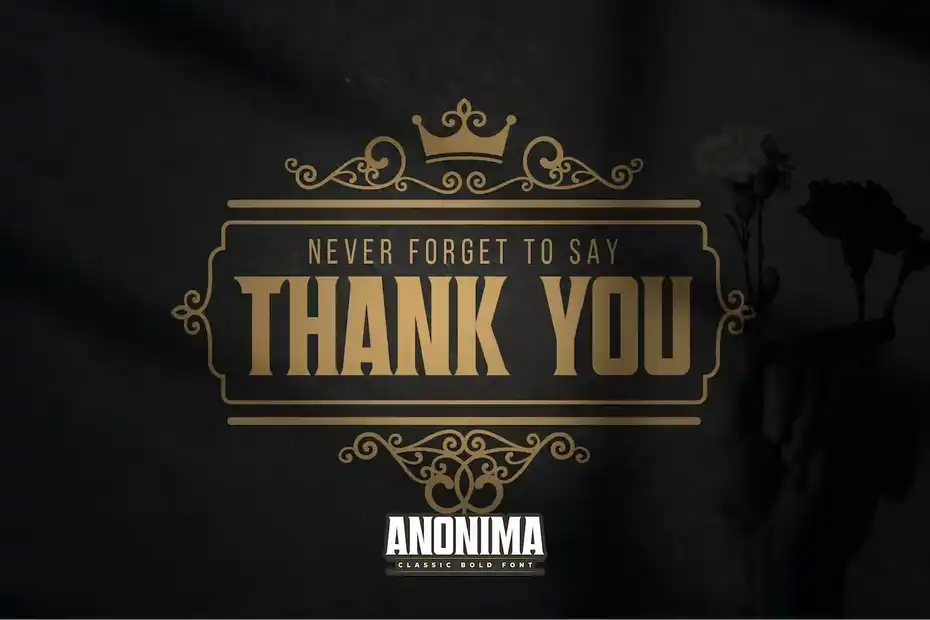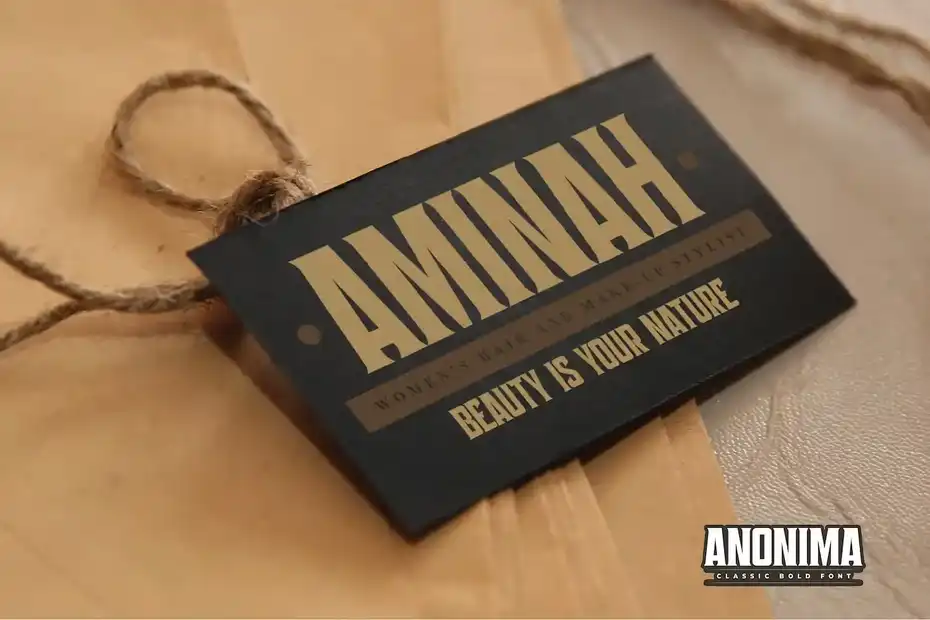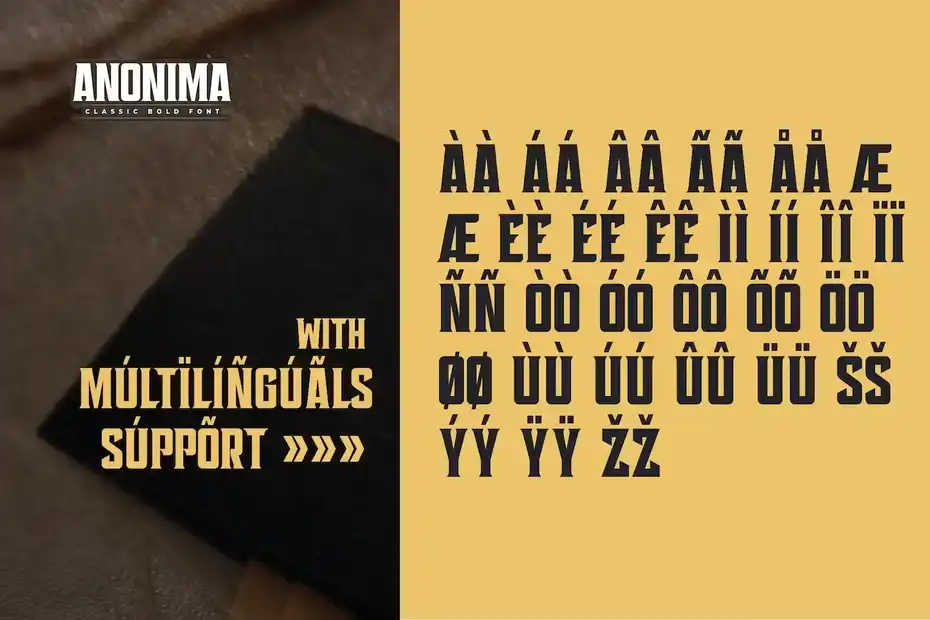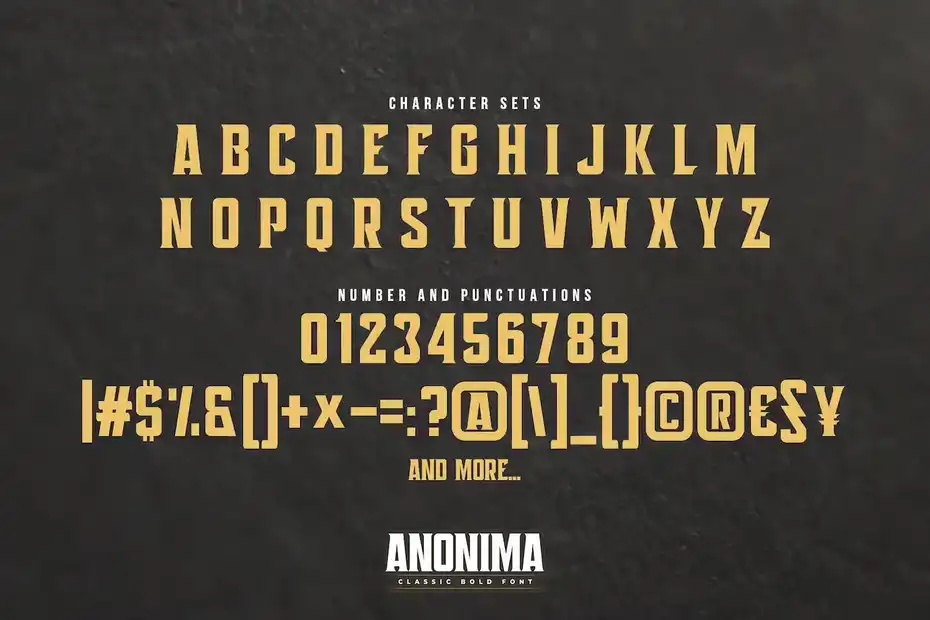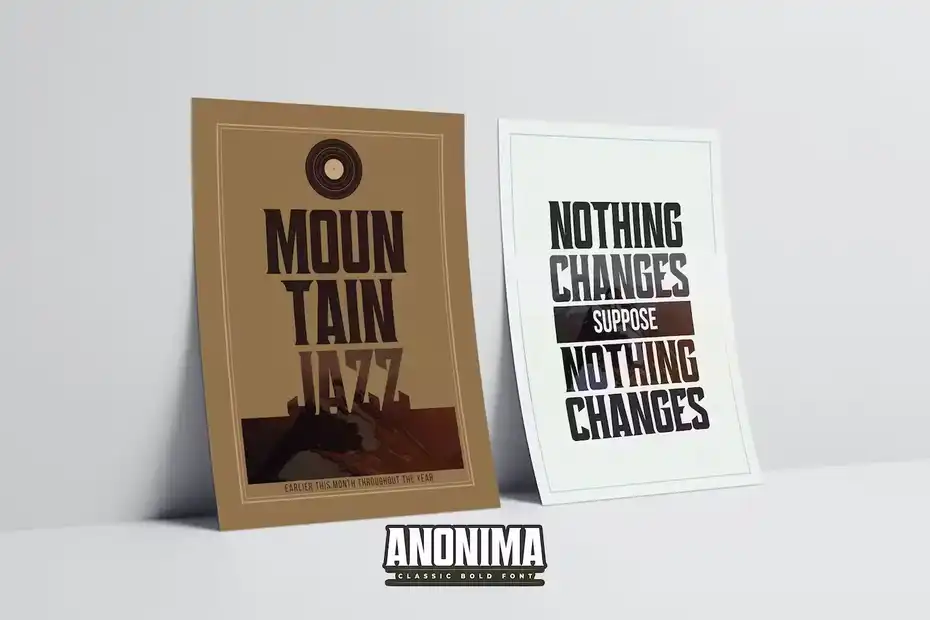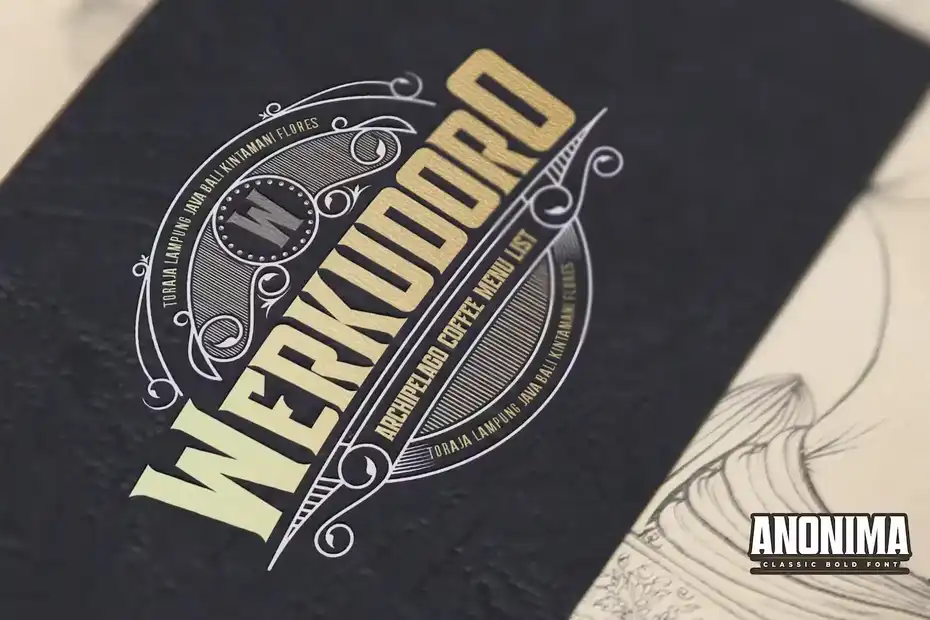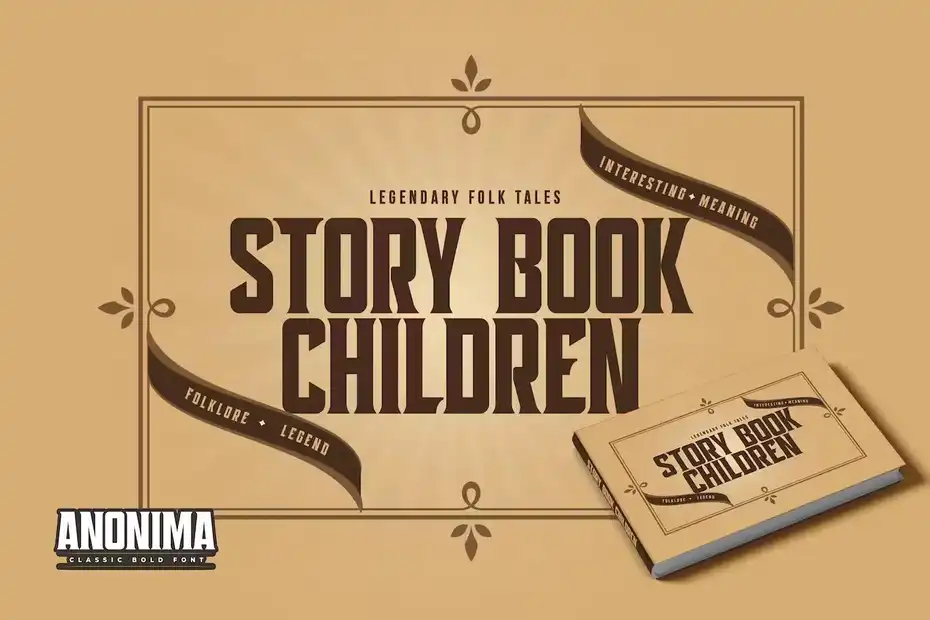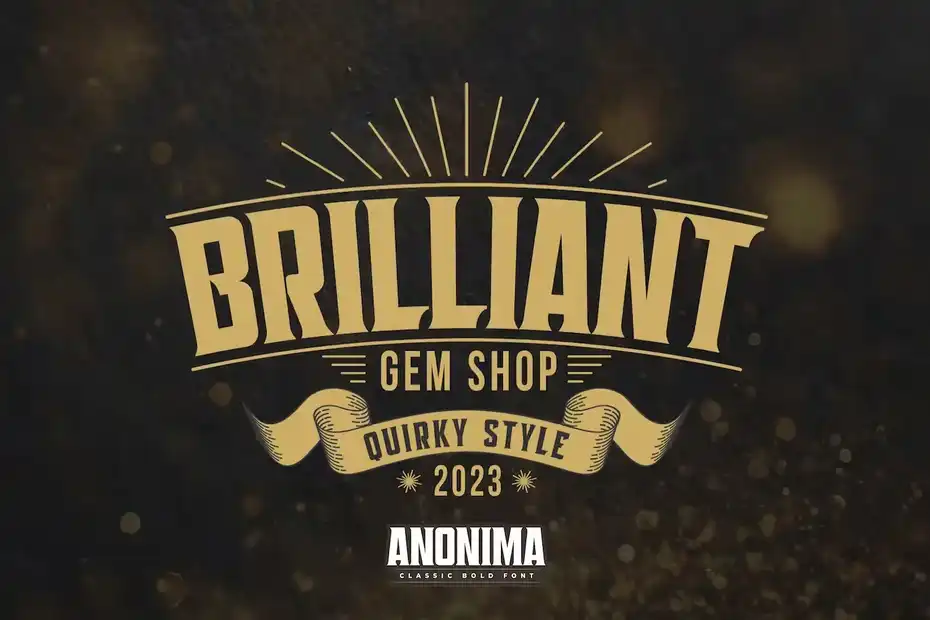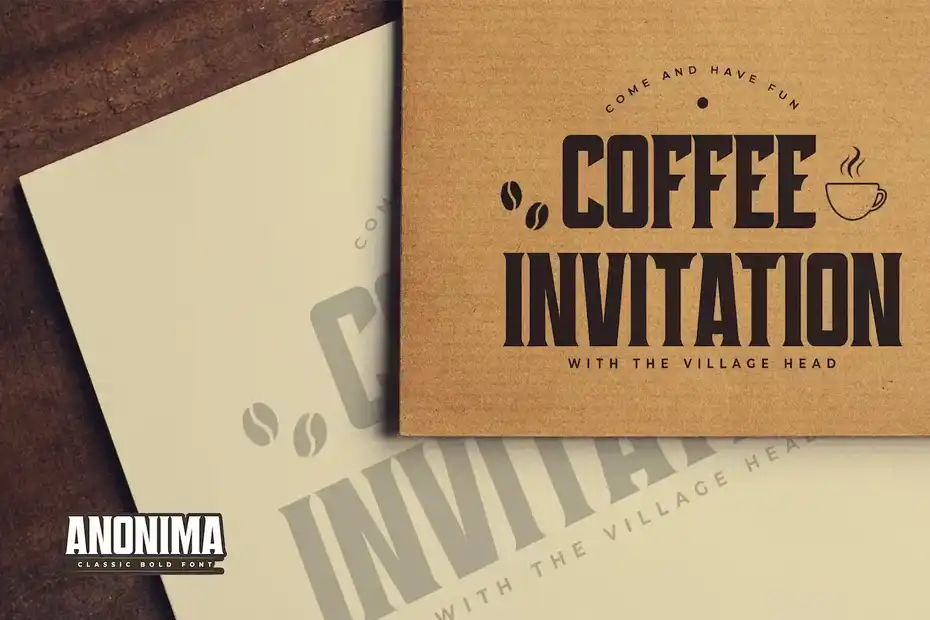
فونت انگلیسی کلاسیک ANONIMA – Classic Bold Serif Font : این مجموعه شامل یک فونت انگلیسی کلاسیک است که برای لوگو، برندینگ، نقل قول، دعوت نامه، بسته بندی محصول، پوستر، تبلیغات، کارت عروسی، برچسب و غیره مناسب میباشد.
• سبک: Serif